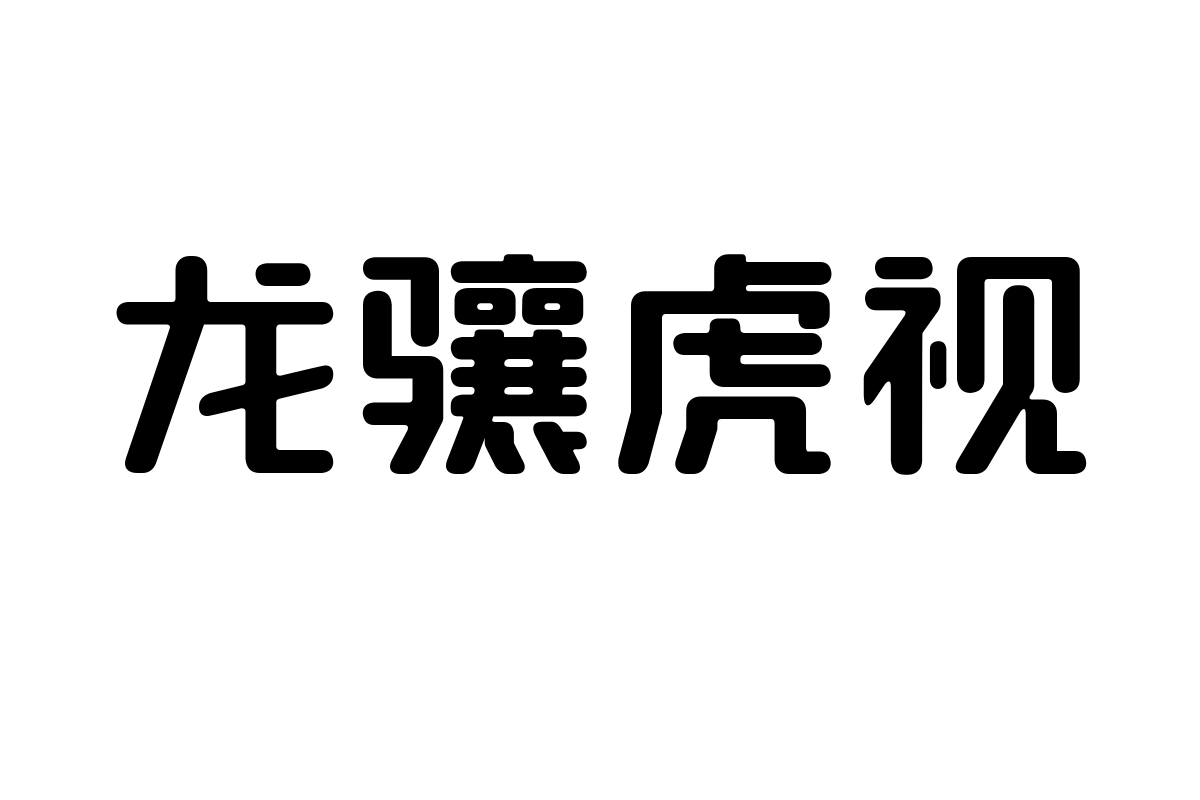
造字工房方圆体是一套由方正字库推出的中文字体,具有独特的设计风格和特点。该字体采用了现代设计元素,结合了传统汉字的结构和形态,创造出一种新颖而富有艺术感的视觉体验。
造字工房方圆体的特点在于其笔画的圆润和流畅性,使得整个字体看起来更加和谐、自然。同时,该字体还注重细节的处理,如笔画的粗细变化、结构的紧凑程度等,都经过精心设计和调整,以呈现出最佳的视觉效果。
此外,造字工房方圆体还具有一定的可读性和实用性,适用于各种应用场景,包括广告设计、包装印刷、书籍装帧等。它的应用范围广泛,能够满足不同用户的需求。
总之,造字工房方圆体是一款独特而富有创意的中文字体,具有很高的艺术价值和实用价值。